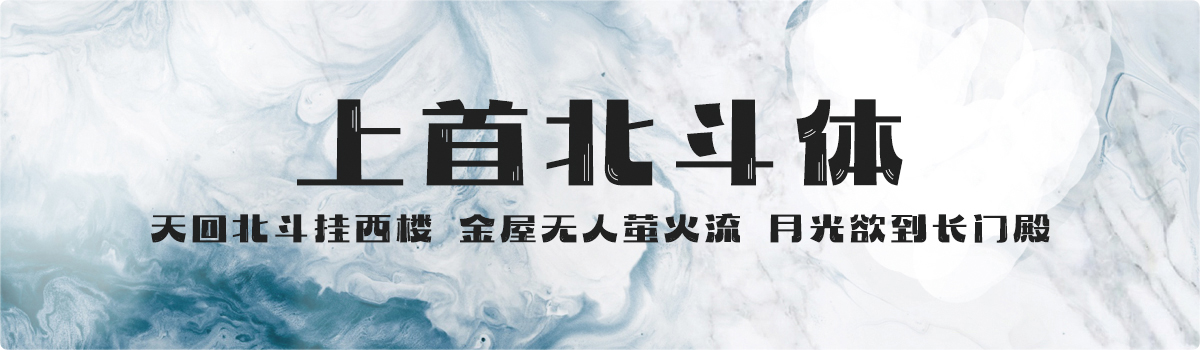
上首北斗体
上首北斗体,这款字体结构工整、笔画清晰,兼顾美观与易读性,适用于标题、正文、海报、包装、LOGO 等多种场景。字形优雅稳定,风格百搭耐看,适配日常排版与创意设计,让文字呈现更舒适、更具质感。上首北斗体一笔一画,皆是细节,以均衡的比例、流畅的线条打造舒适视觉体验,字形端正大气,风格简约现代。无论是商业设计、品牌宣传还是日常排版,都能轻松驾驭,让文字更有格调与力量。上首北斗体字体下载。